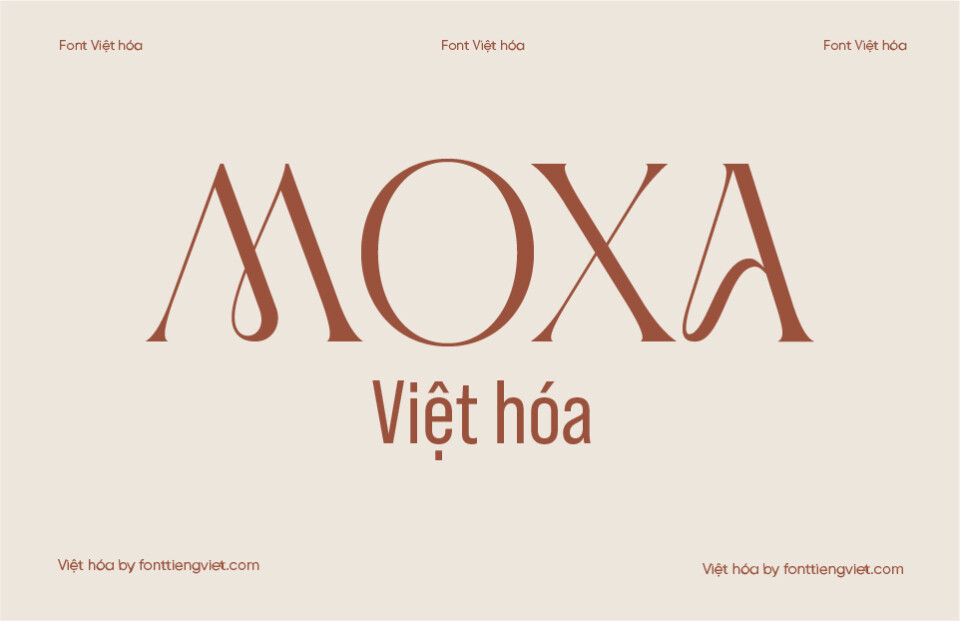
Font Việt hóa 1FTV VIP Moxa Bestine
Trong thế giới đồ họa hiện đại việc lựa chọn một bộ Font Việt hóa 1FTV VIP Moxa Bestine chất lượng là yếu tố then chốt giúp các tác phẩm trở nên ấn tượng và thu hút hơn bao giờ hết. Đối với những người làm sáng tạo đặc biệt là các bạn học sinh và sinh viên việc tìm kiếm một mẫu Font Miễn Phí nhưng vẫn đảm bảo đầy đủ tính năng hỗ trợ tiếng Việt có dấu luôn là ưu tiên hàng đầu. Bộ phông chữ Moxa Bestine phiên bản 1FTV VIP không chỉ sở hữu vẻ đẹp thanh lịch tinh tế mà còn được tối ưu hóa hoàn toàn cho bảng mã Unicode giúp quá trình gõ văn bản trở nên thuận tiện và không xảy ra lỗi hiển thị. Đây là một công cụ hỗ trợ đắc lực cho các bài thuyết trình thiết kế bìa sách hay những dự án học đường đòi hỏi tính thẩm mỹ cao và sự chuyên nghiệp tuyệt đối.
Đặc điểm nổi bật của Font Việt hóa 1FTV VIP Moxa Bestine
Phong cách thiết kế sang trọng và hiện đại
Mẫu phông chữ này mang trong mình sự kết hợp hoàn hảo giữa nét chữ Script uyển chuyển và phong cách Serif cổ điển tạo nên một diện mạo vô cùng độc đáo. Font Việt hóa 1FTV VIP Moxa Bestine được thiết kế với những đường nét mềm mại nhưng vẫn giữ được cấu trúc vững chãi giúp người xem cảm nhận được sự tỉ mỉ trong từng chi tiết. Với độ tương phản cao giữa các nét thanh và nét đậm bộ phông này cực kỳ phù hợp cho các tiêu đề lớn biển quảng cáo hoặc các dòng chữ cần tạo điểm nhấn mạnh mẽ. Sự đa dạng trong cách thể hiện giúp nó có thể ứng dụng linh hoạt từ những thiết kế mang tính trang trọng lịch sự đến những sản phẩm mang hơi hướng nghệ thuật phá cách.
Khả năng tương thích và tối ưu hóa tiếng Việt
Một trong những điểm cộng lớn nhất của phiên bản 1FTV VIP chính là việc Việt hóa cực kỳ bài bản. Các dấu câu như huyền sắc hỏi ngã nặng hay các chữ cái đặc biệt như ă â đ ê ô ơ ư đều được tinh chỉnh về khoảng cách và kích thước để hài hòa với tổng thể chữ cái gốc. Điều này giúp Font Việt hóa 1FTV VIP Moxa Bestine không bị mất đi linh hồn của bản thiết kế nguyên bản đồng thời vẫn đảm bảo tính dễ đọc và thẩm mỹ cho người dùng Việt Nam. Bạn sẽ không còn phải lo lắng về việc các dấu bị dính vào nhau hay đặt sai vị trí thường thấy ở các bản Việt hóa kém chất lượng trên thị trường hiện nay.
Ứng dụng thực tế của Font Việt hóa 1FTV VIP Moxa Bestine trong học tập
Thiết kế slide bài giảng và báo cáo học thuật
Đối với các bạn học sinh và giáo viên việc trình bày nội dung sao cho bắt mắt là rất quan trọng để thu hút sự chú ý. Sử dụng Font Việt hóa 1FTV VIP Moxa Bestine cho các tiêu đề chính trong slide Powerpoint sẽ giúp bài giảng trở nên sinh động và chuyên nghiệp hơn hẳn các phông chữ hệ thống thông thường. Độ sắc nét của phông chữ này cũng giúp cho việc trình chiếu trên máy chiếu hay màn hình lớn luôn đạt hiệu quả hiển thị tốt nhất đảm bảo mọi học sinh ở cuối lớp vẫn có thể theo dõi nội dung một cách rõ ràng.
Sáng tạo thiệp mời và ấn phẩm truyền thông trường học
Vào các dịp lễ hội hay sự kiện của nhà trường bộ phông chữ này là lựa chọn tuyệt vời để thiết kế thiệp mời băng rôn hay các tấm áp phích cổ động. Với vẻ ngoài sang trọng nó giúp nâng tầm giá trị của các ấn phẩm truyền thông mang lại cảm giác chỉn chu và tôn trọng đối với người nhận. Ngoài ra việc sử dụng phông chữ đẹp còn khơi gợi niềm đam mê hội họa và tư duy thẩm mỹ cho các em học sinh ngay từ khi ngồi trên ghế nhà trường.